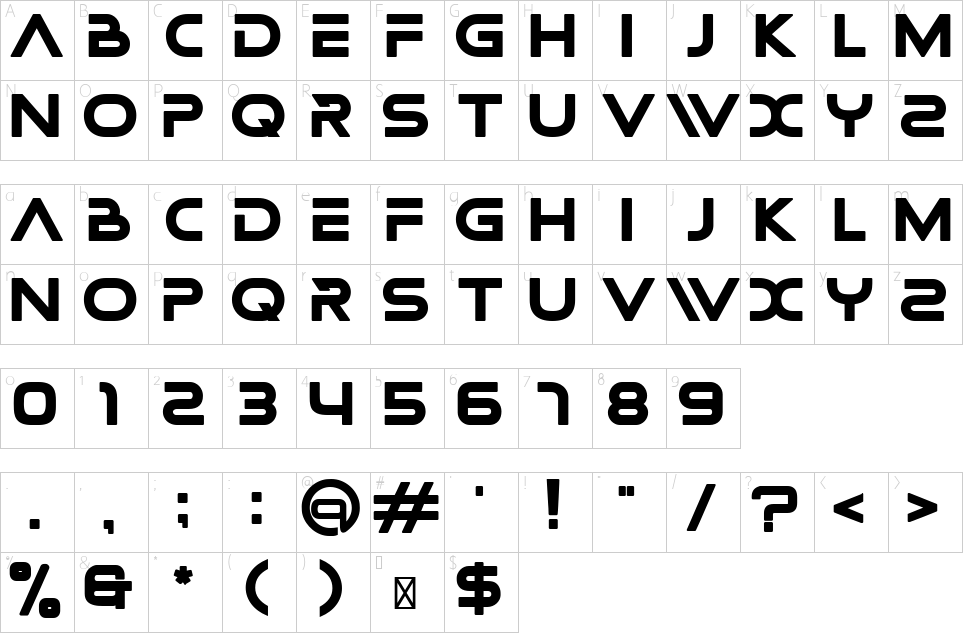
Aristotle Font
Descubra o mundo fascinante da fonte ‘Aristotle’ para seus projetos digitais. Com uma elegância única e um toque moderno, a ‘Aristotle Font’ foi criada pela 177Studio.com. Esta fonte já foi baixada 3,215 vezes, demonstrando seu valor e popularidade. Composta com precisão e sofisticação, a ‘Aristotle Font’ é ideal para qualquer projeto que busque uma aparência sofisticada e única. Seja para websites, design gráfico, material educacional ou qualquer outro uso, a ‘Aristotle Font’ é uma escolha inovadora para tornar seu design ainda mais especial. Download agora e experimente a diferença desta fonte na sua próxima criação.